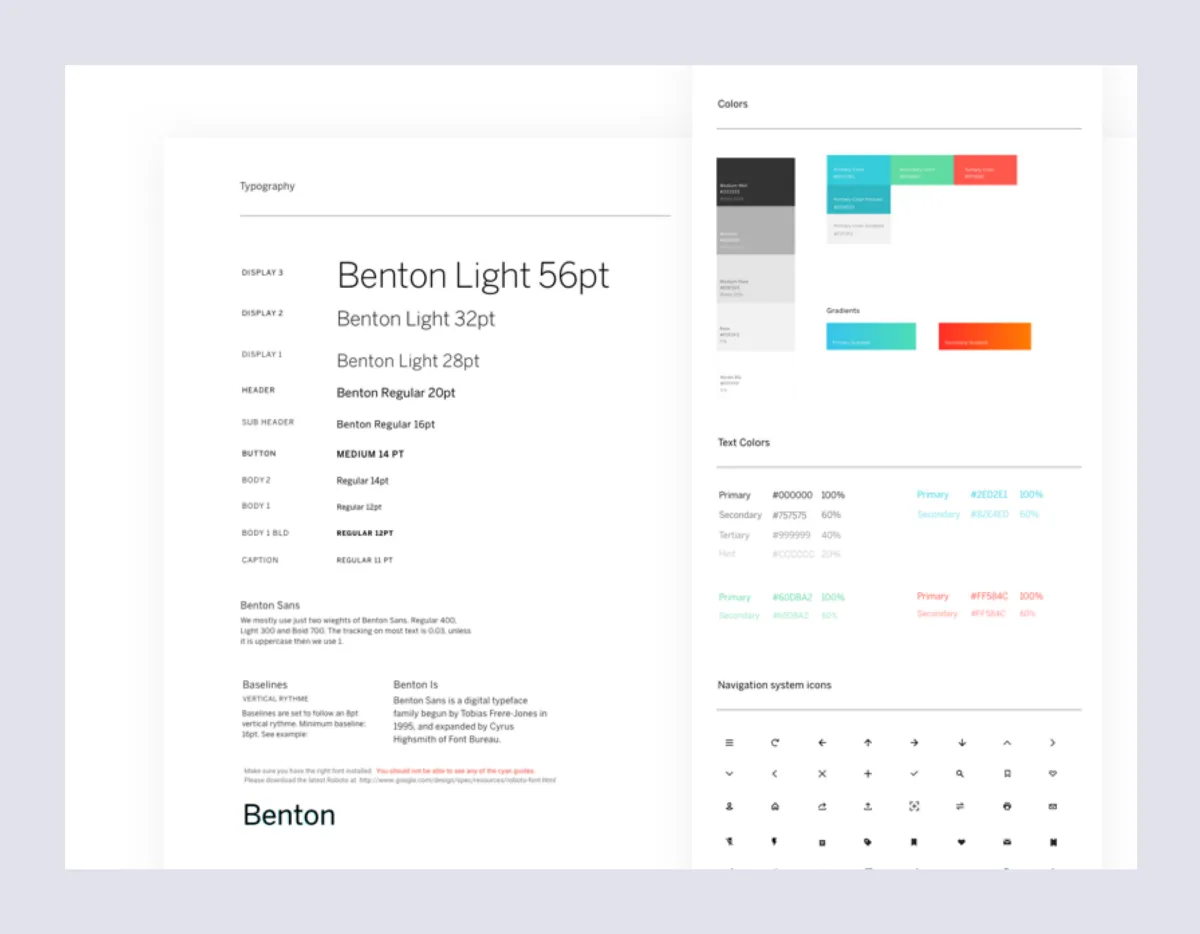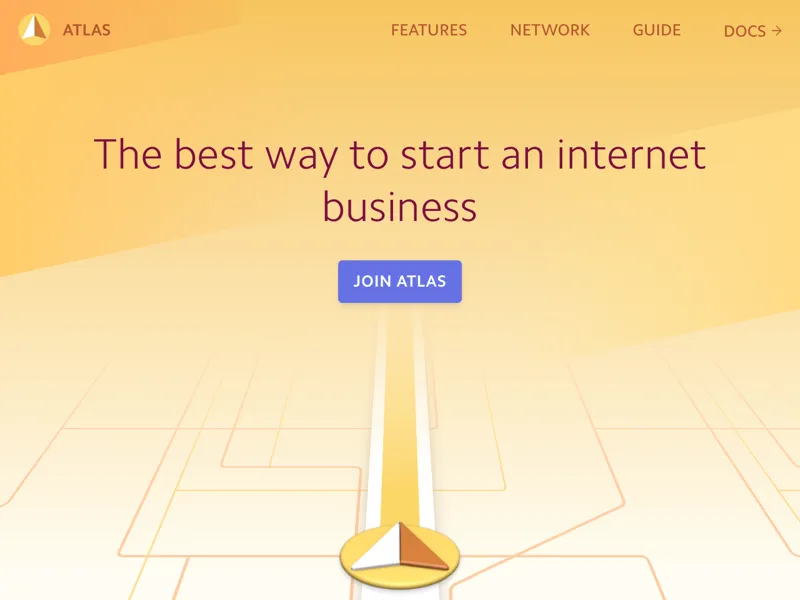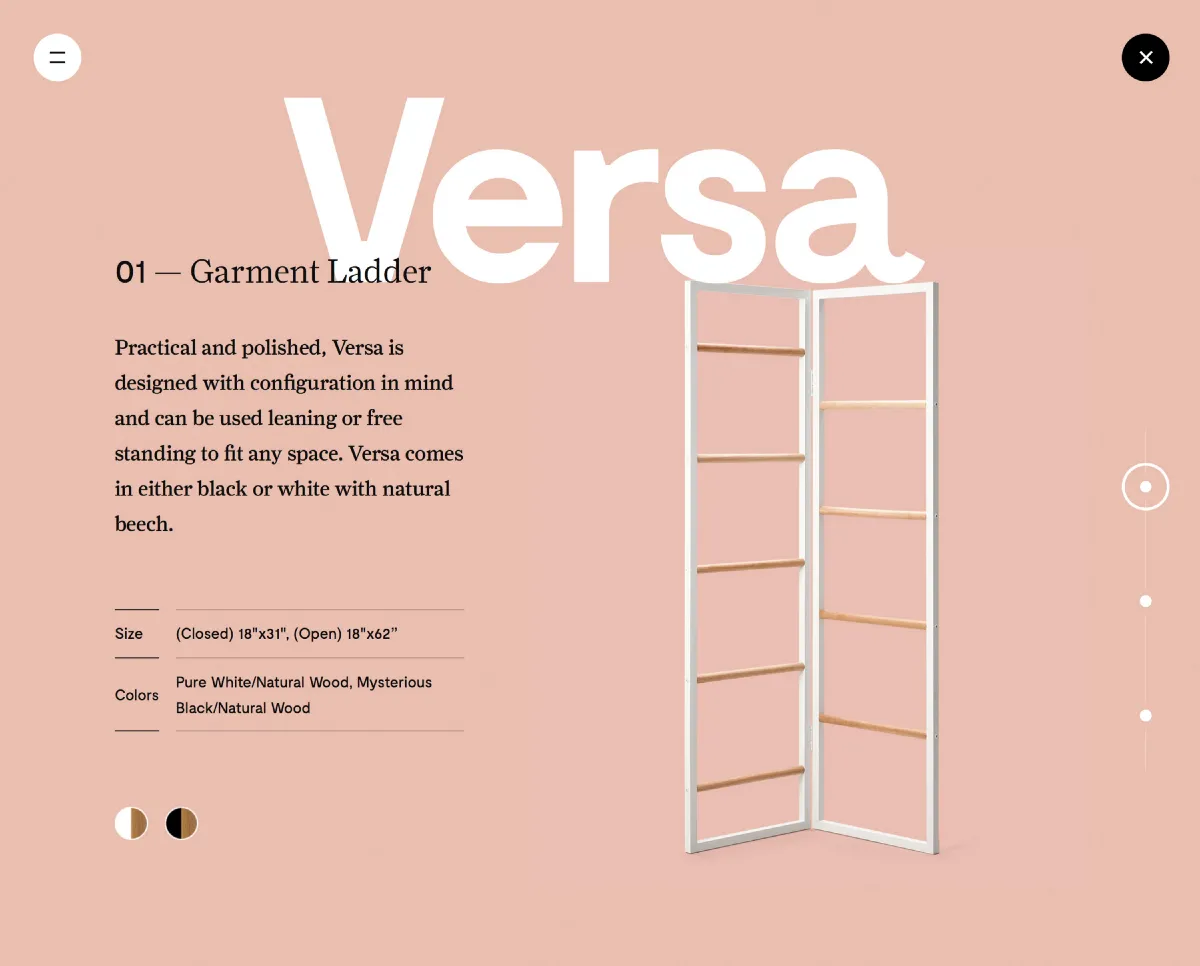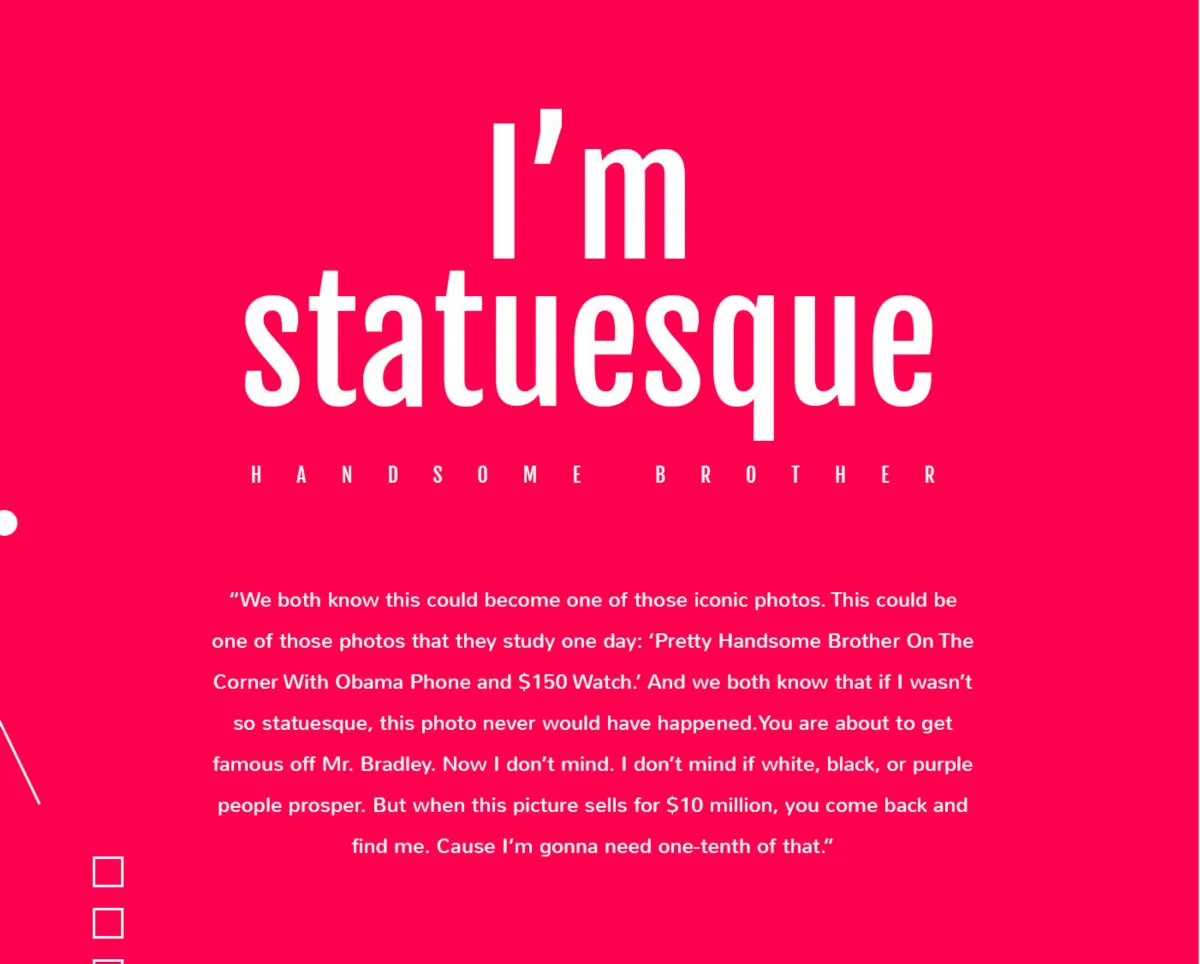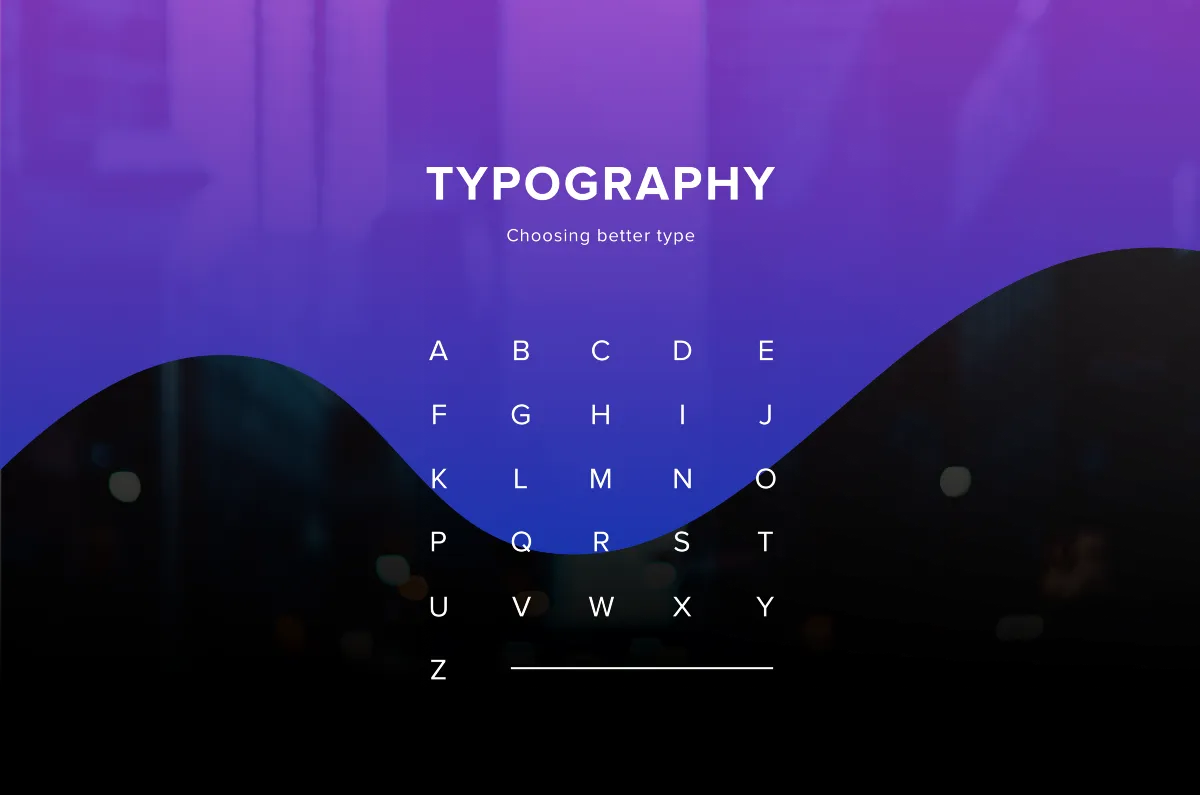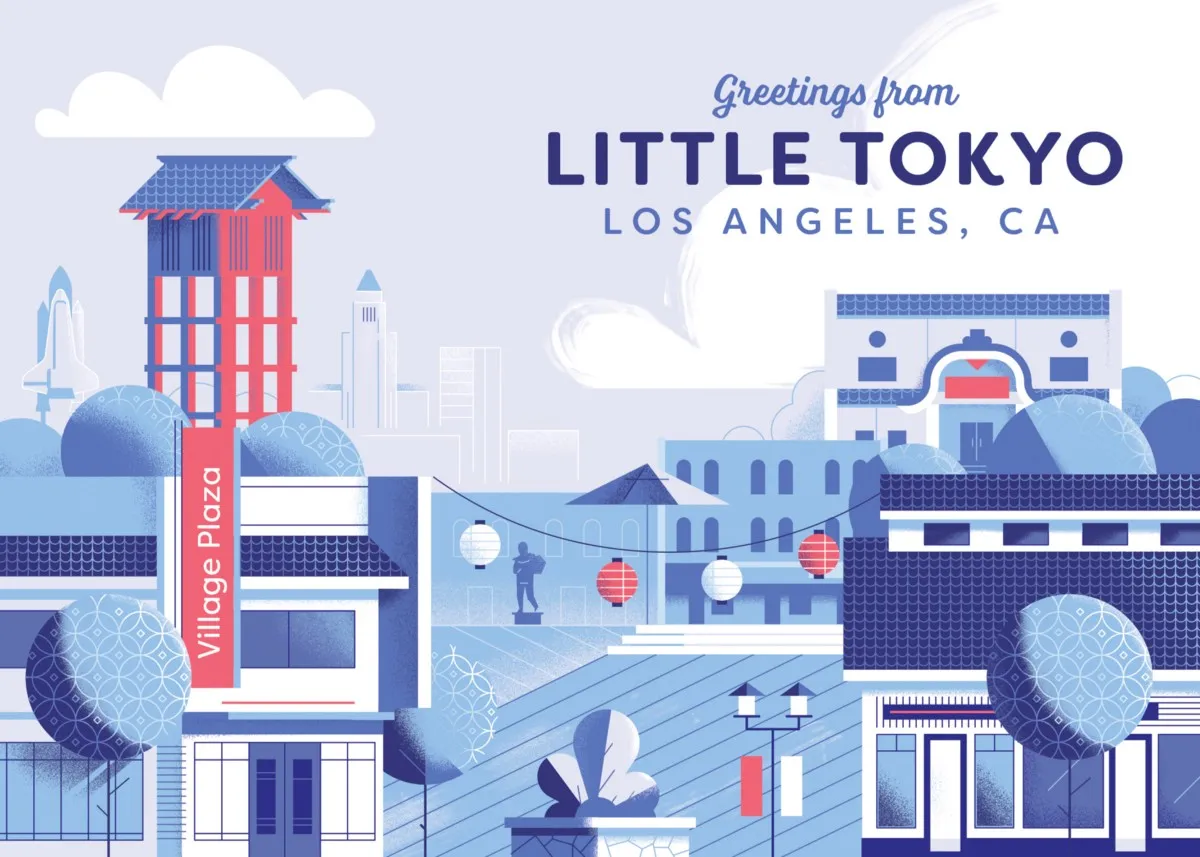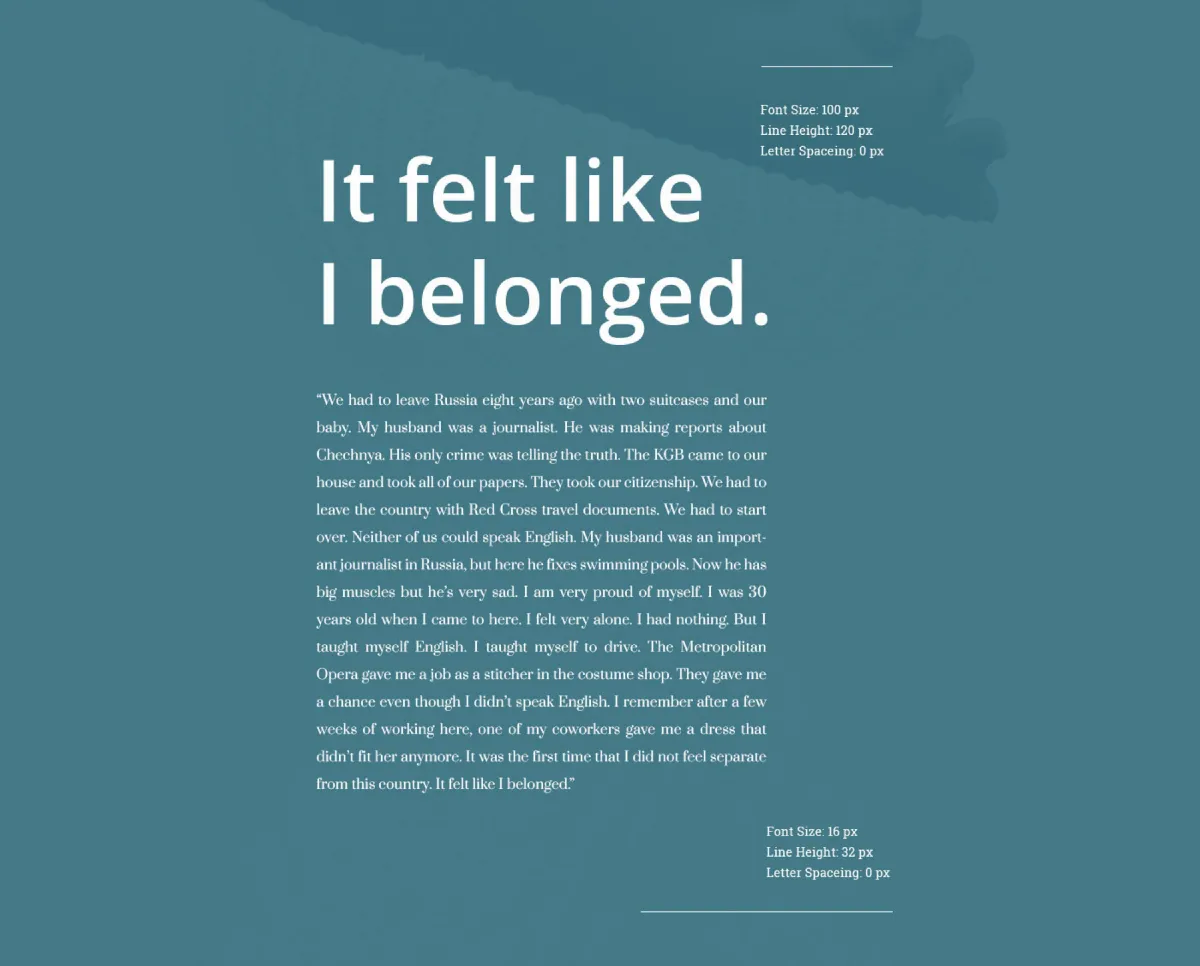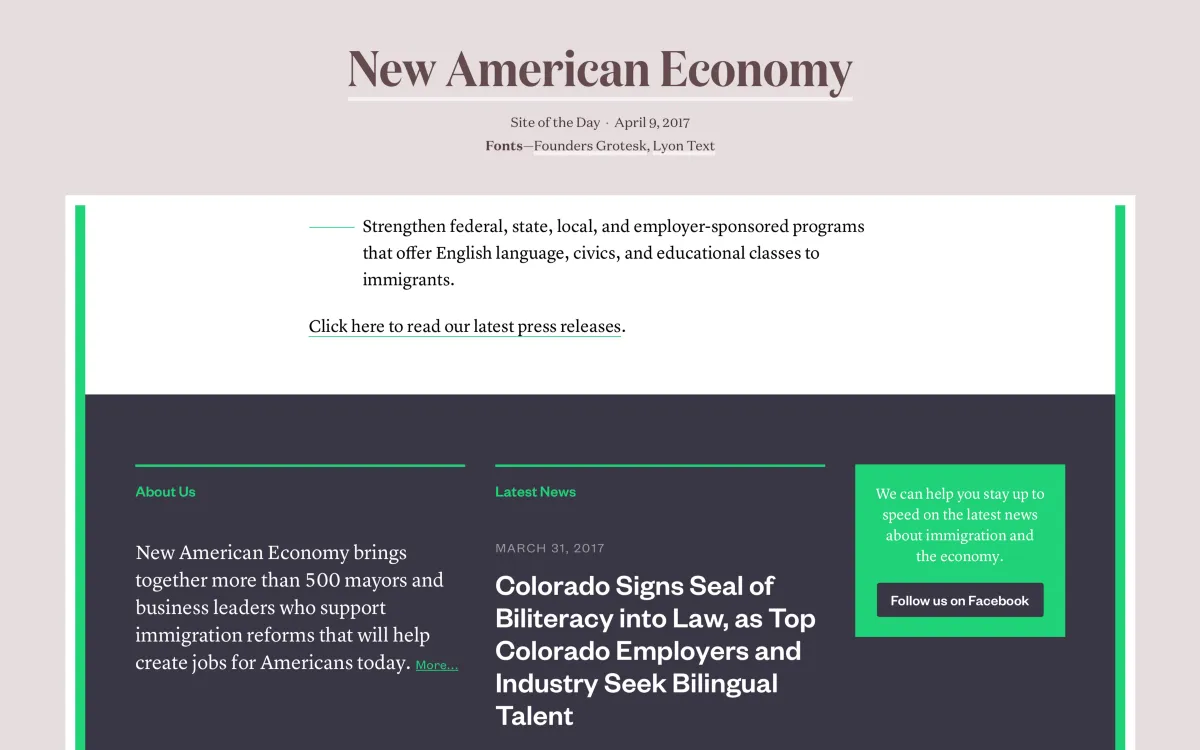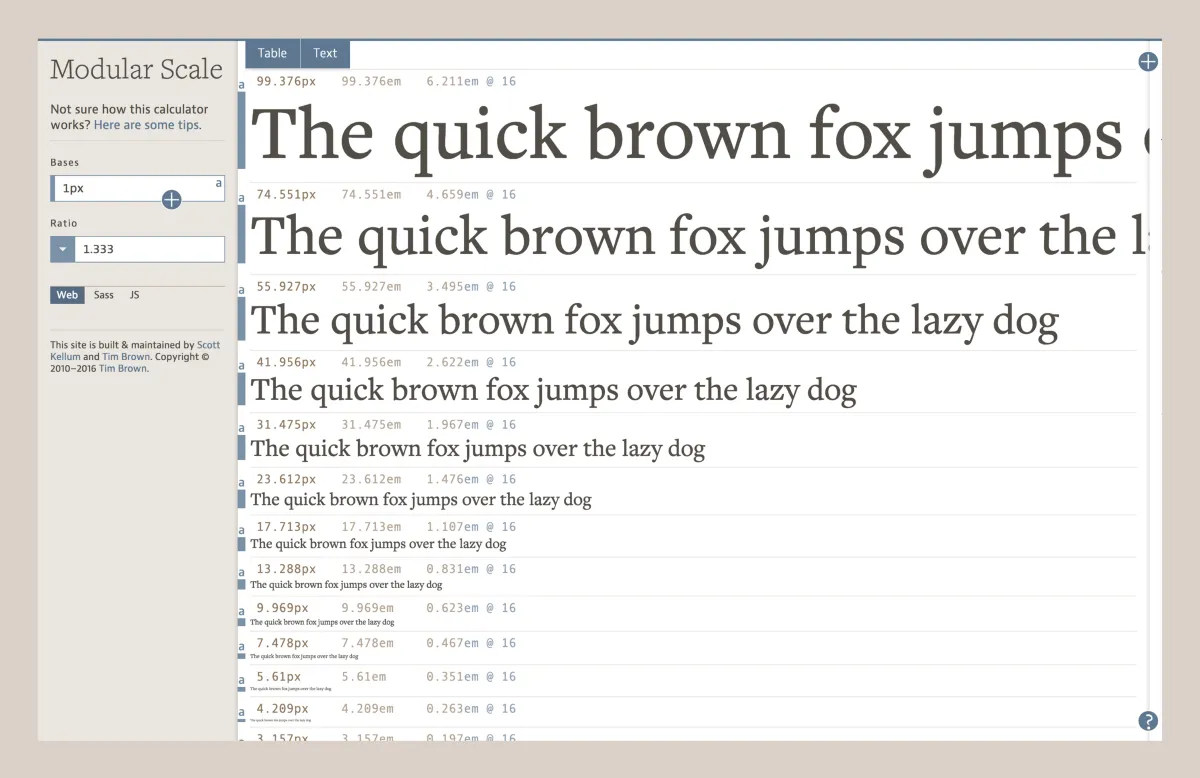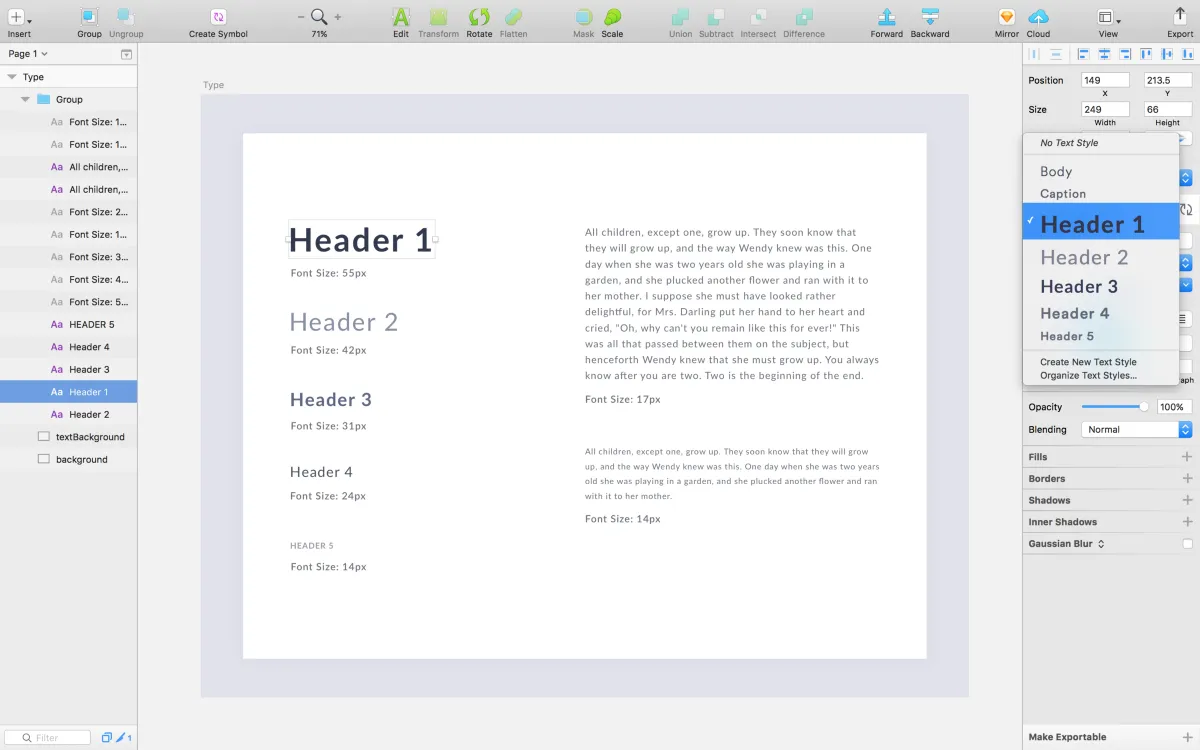
Tipografia: um processo para escolher fontes
Escolher fontes é um processo custoso e complexo, que exige experiência (e talvez uma pitada de talento). Para escolher a fonte certa — ou, para ser mais técnico, o tipo certo — para o design certo é tarefa difícil, complexa.
Para facilitar, disponibilizamos este guia com um processo para escolher fontes para que você possa ficar ciente de algumas técnicas e métodos necessários para um bom match entre fonte e design.
Processo para escolher fontes: imagem bonita com todas as letras do alfabeto
Uma das habilidades mais importantes que você pode aprender como designer é como escolher a tipografia (ou como escolher fontes). Isso ocorre porque o texto é uma das principais maneiras pelas quais designers podem se comunicar com as pessoas. A tipografia pode fazer ou quebrar um design.
Há beleza e complexidade na tipografia. Algumas pessoas dedicam suas carreiras inteiras a tipos. Felizmente, o trabalho delas está bem documentado, por isso temos toneladas de recursos online para tipografia.  :-)
Este artigo foi concebido para servir como ponto de partida para ajudar você a aprender como escolher o tipo de seus projetos. Ele incentivará você a explorar fontes e combinações de fontes além daquelas com as quais você está familiarizado.
Identifique seu propósito
Antes de fazer qualquer outra coisa, primeiro identifique o propósito do seu projeto. Quais informações você deseja transmitir? Qual é o meio para o seu design?
Um bom design alinha tipografia com finalidade. Isso ocorre porque a tipografia é fundamental para definir o humor, o tom e o estilo em seus designs.
Por exemplo, se você estiver criando um cartão comemorativo com uma ilustração pesada, escolha uma fonte que se ajuste ao estilo da ilustração. Harmonize a fonte com o resto do design.
Processo para escolher fontes: exemplo de como aplicar uma fonte de maneira harmoniosa.
Se você está projetando uma página de destino (landing page) com enfoque mais visual, escolha uma fonte simples que não prejudique suas imagens. Use o tipo como forma de enfatizar informações para comunicar o significado.
Processo para escolher fontes: exemplo de landing page
Se imagens são o foco, escolha fontes simples para que elas tenham destaque.
Identifique seu público
Depois de determinar o objetivo do design, identifique seu público. Este passo no processo de escolher uma fonte é crucial porque a idade, interesse etc. influenciarão as opções de fonte.
Depois de esclarecer o propósito do design, identifique seu público. Essa etapa é crucial, pois as informações sobre seus público-alvo, como idade, interesses e aspectos culturais, podem influenciar as decisões que você toma sobre tipografia.
Por exemplo, algumas fontes são mais apropriadas para crianças. Ao aprender a ler, as crianças precisam de fontes altamente legíveis com formas de letra generosas. Um bom exemplo disso é a fonte Sassoon Primary.
Sassoon Primary foi desenvolvida por Rosemary Sassoon a partir de sua pesquisa sobre o tipo de letras que as crianças acharam fácil de ler.
Processo para escolher fontes: exemplo da fonte Rosemary Sassoon
Outras fontes são mais apropriadas para idosos: fontes amigáveis para uso sênior usam tamanhos legíveis, cores de alto contraste e evitam estilos decorativos.
Ao escolher o tipo, leve em consideração seu público e suas necessidades. Simplificando, tenha empatia com seu público.
Procure inspiração ao escolher fontes
Veja o trabalho de outros designers. Tente entender como eles tomaram suas decisões.
Inspiração de fontes
Para inspiração, The 100 Best Free Fonts  é um ótimo artigo para colocar você na mentalidade certa para escolher tipos. No artigo, CreativeBloq explica as motivações por trás de cada fonte.
Outro recurso útil é o 100 Greatest Free Fonts Collection for 2015  da Awwwards.
O Invision também compilou um gigantesco repositório de recursos de tipografia. Você encontrará muitas fontes de inspiração lá.
Processo para escolher fontes: screenshot do site Typ.io
Typ.io, para inspiração de fontes
Para inspiração de sites reais, confira Typ.io. O site seleciona a inspiração da fonte em toda a web. Além disso, o site fornece definições de fontes CSS na parte inferior de cada amostra de inspiração.
Além de procurar em sites dedicados de inspiração para fontes (que, certamente, ajuda muito ao escolher fontes), visite seus sites favoritos e confira as fontes que eles usam.
Uma boa ferramenta para isso é WhatTheFont. WhatTheFont é uma extensão do Chrome que permite inspecionar as fontes da web passando o mouse sobre elas.
Aliás, já citamos ele aqui no dpw, em nosso artigo sobre identificadores de fontes.
Inspiração para emparelhamento de fontes
Mas é preciso ir além de somente escolher as fontes; é preciso também a atenção/inspiração para emparelhamento de fontes. O emparelhamento de fontes é tão importante quanto as próprias fontes.
Repetindo para dar ênfase, tipografia é sobre experimentação; é ao mesmo tempo ciência e arte.
Se fosse fácil escolher fontes para projetos de design e web, todos fariam isso muito bem, certo? Mas, voltando ao mundo real, trata-se de um processo bastante complexo, que demanda muito esforço e estudo para ser feito com maestria.
Processo este que, caso queira, você deve dominar através de muita prática e experimentação.
Desafiamos você a sair da sua zona de conforto e explorar mais possibilidades de fontes em seu designs!